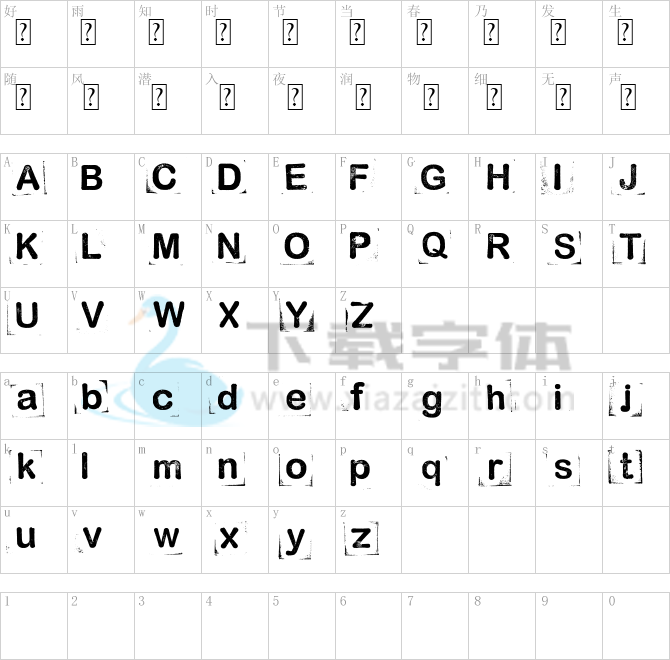
Anal-probe.ttf字体下载
Anal-probe.ttf字体下载,这款字体结构工整、笔画清晰,兼顾美观与易读性,适用于标题、正文、海报、包装、LOGO 等多种场景。字形优雅稳定,风格百搭耐看,适配日常排版与创意设计,让文字呈现更舒适、更具质感。Anal-probe.ttf字体下载一笔一画,皆是细节,以均衡的比例、流畅的线条打造舒适视觉体验,字形端正大气,风格简约现代。无论是商业设计、品牌宣传还是日常排版,都能轻松驾驭,让文字更有格调与力量。Anal-probe.ttf字体下载字体下载。
Anal-probe.ttf图片展示
Anal-probe.ttf字体属性详情
• 字体名称:Anal-probe
• 字体标识 ID:MikeLarsson: Anal-probe: 2012
• 字体全名:Anal-probe
• 版本说明:Version 1.00 October 30, 2012, Another rubber-stamp release
Anal-probe.ttf映射图